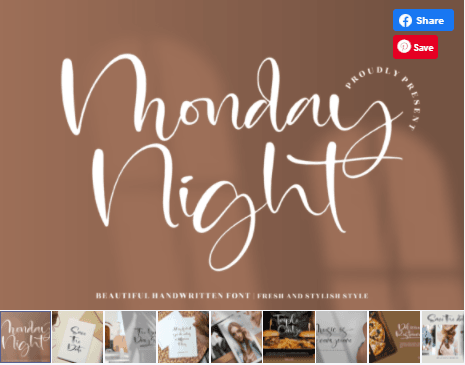
Monday Night Font
Monday Night - это романтичный и сладкий каллиграфический шрифт с персонажами, танцующими вдоль базовой линии. Он придаст изюминку любому дизайнерскому проекту, который вы желаете создать! Monday Night закодирован в кодировке PUA, что означает, что вы можете легко получить доступ ко всем глифам и росчеркам!